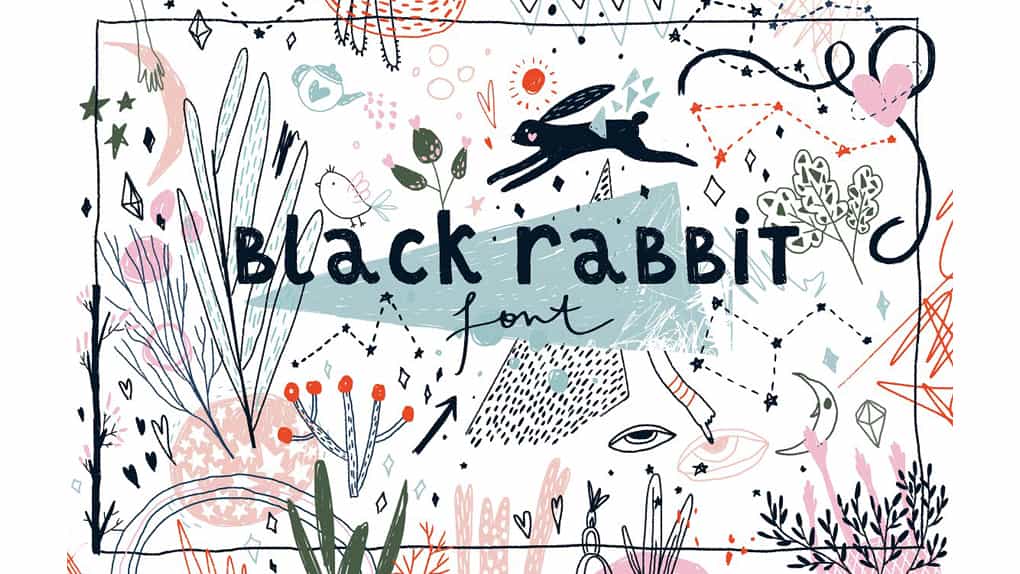
فونت انگلیسی فانتزی – Black Rabbit Font
فونت انگلیسی فانتزی : فونت آماده شده در این پست بسیار جذاب و دارای بافتی خشن و جادویی است. فقط کافی است تصاویر آزمایشی مربوط به فونت را ببینید تا در مورد نمونه های استفاده از نوع متن ایده بگیرید.